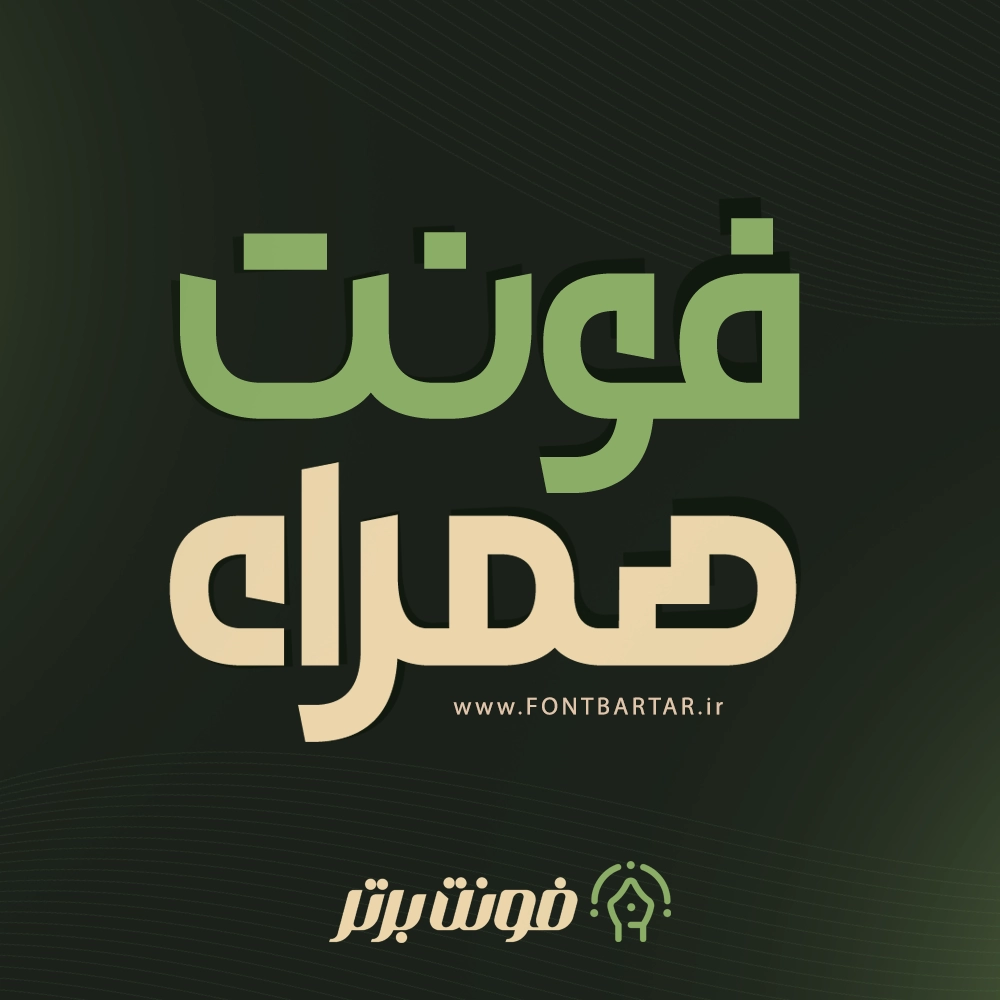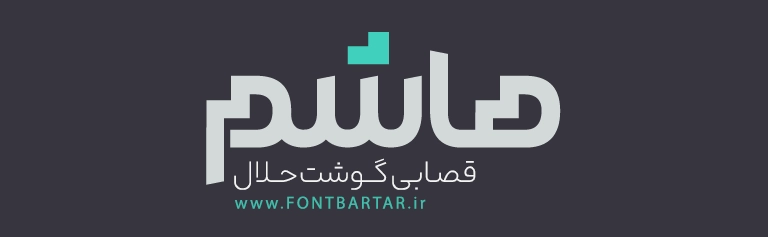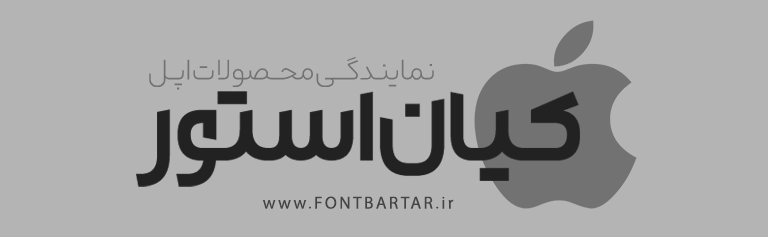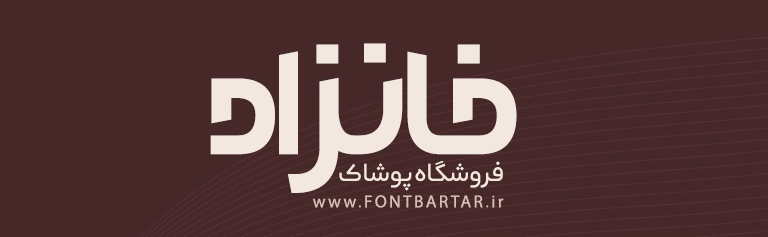
دانلود فونت همراه | فونت فارسی مدرن و جذاب برای طراحی حرفهای
فونت زیبا همراه یکی از جدید ترین و خاص ترین فونت های فارسی است که با طراحی مدرن، خوانایی بالا و ساختاری قدرتمند، انتخابی فوقالعاده برای طراحان، تولیدکنندگان محتوا و صاحبان کسبوکارهای دیجیتال محسوب میشود. این فونت خاص با استایل نرم، ضخامت استاندارد و فرم هندسی جذاب، برای ساخت تیتر، پوستر، بنر، کاور محتوا، سوشال مدیا و لوگوتایپ فوقالعاده کاربردی است.
ویژگیهای فونت زیبا همراه
خرید فونت زیبا همراه با هدف استفاده در حوزههای مختلف طراحی دیجیتال ساخته شده و ویژگیهای زیر آن را تبدیل به یک انتخاب حرفهای کرده است:
- ✔️ استایل مدرن و چشمنواز
- ✔️ مناسب برای طراحی لوگوتایپ و عنوانهای تبلیغاتی
- ✔️ دارای فرم هندسی قدرتمند و منحنیهای نرم
- ✔️ وزن مناسب برای خوانایی بالا در صفحات دیجیتال
- ✔️ قابل استفاده در طراحی گرافیک، صفحات وب و اپلیکیشن
کاربردهای فونت همراه
فونت همراه به دلیل ساختار خاص و جذاب خود در پروژههای زیر بیشترین کارایی را دارد:
- طراحی کاور پستهای اینستاگرام
- ساخت پوسترهای تبلیغاتی
- طراحی لوگوتایپ فارسی
- فونت زیبا برای استوری
- فونت زیبا برای اسم
- تایپوگرافی حرفهای
- تولید بنرهای فروشگاهی
- طراحی رابط کاربری (UI/UX)
- ساخت تامبنیل یوتیوب و آپارات
مزایای استفاده از فونت همراه در طراحی
انتخاب فونت زیبا مناسب میتواند کیفیت یک طراحی را به شکل چشمگیری افزایش دهد. با استفاده از فونت همراه:
- ظاهر پروژه شما مدرنتر و حرفهایتر دیده میشود
- خوانایی متن در صفحات وب و شبکههای اجتماعی افزایش مییابد
- توجه مخاطب به تیترها و پیام اصلی جلب میشود
- برند شما هویت بصری یکپارچهتری پیدا میکند
1. آیا میتوان از فونت همراه در طراحی لوگو استفاده کرد؟
بله، به دلیل ساختار قدرتمند و یکپارچه، این فونت یکی از گزینههای عالی برای طراحی لوگوتایپ است.